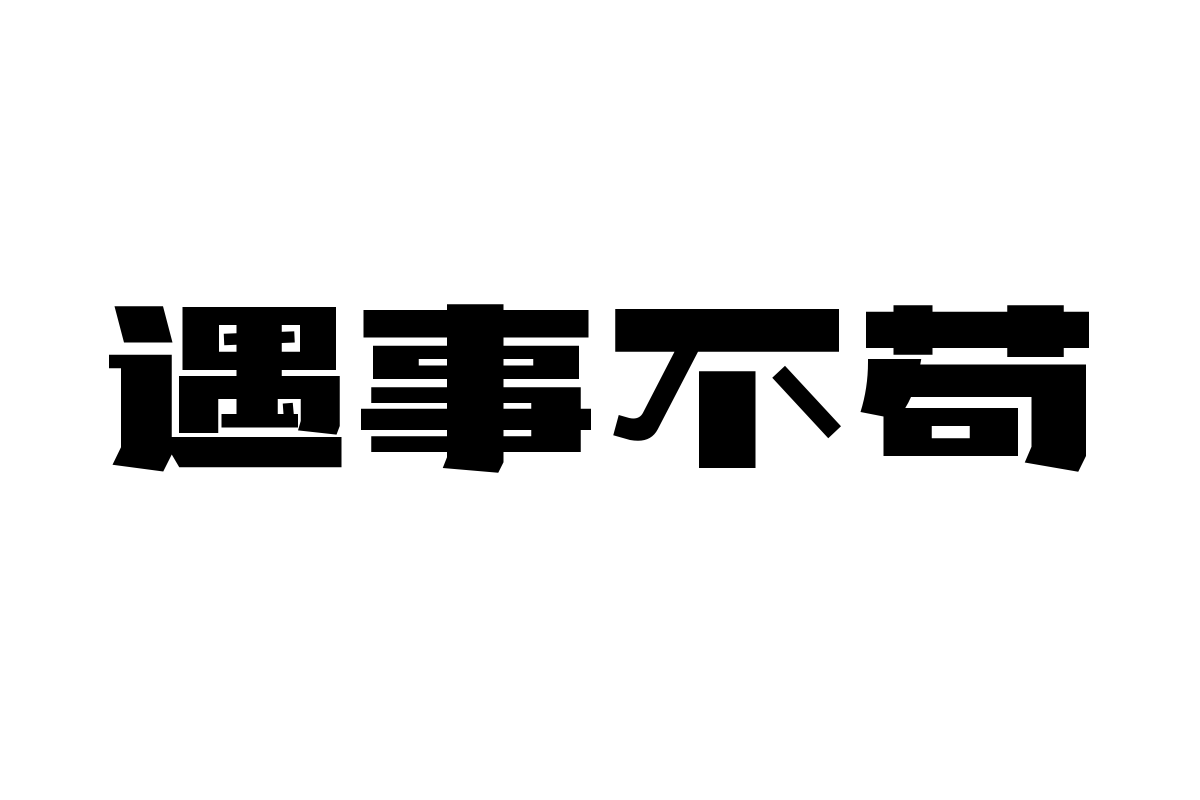
造字工房巧方体是一款具有独特设计感的字体,它采用了独特的方形结构,使得每个字符都呈现出独特的形状和风格。这种设计不仅让字体看起来更加美观,也使得它在视觉上具有很高的辨识度。
造字工房巧方体的特点在于它的方形结构,这使得每个字符都呈现出独特的形状和风格。这种设计不仅让字体看起来更加美观,也使得它在视觉上具有很高的辨识度。同时,这款字体还具有一定的艺术感,适合用于各种设计场景,如广告、海报、包装等。